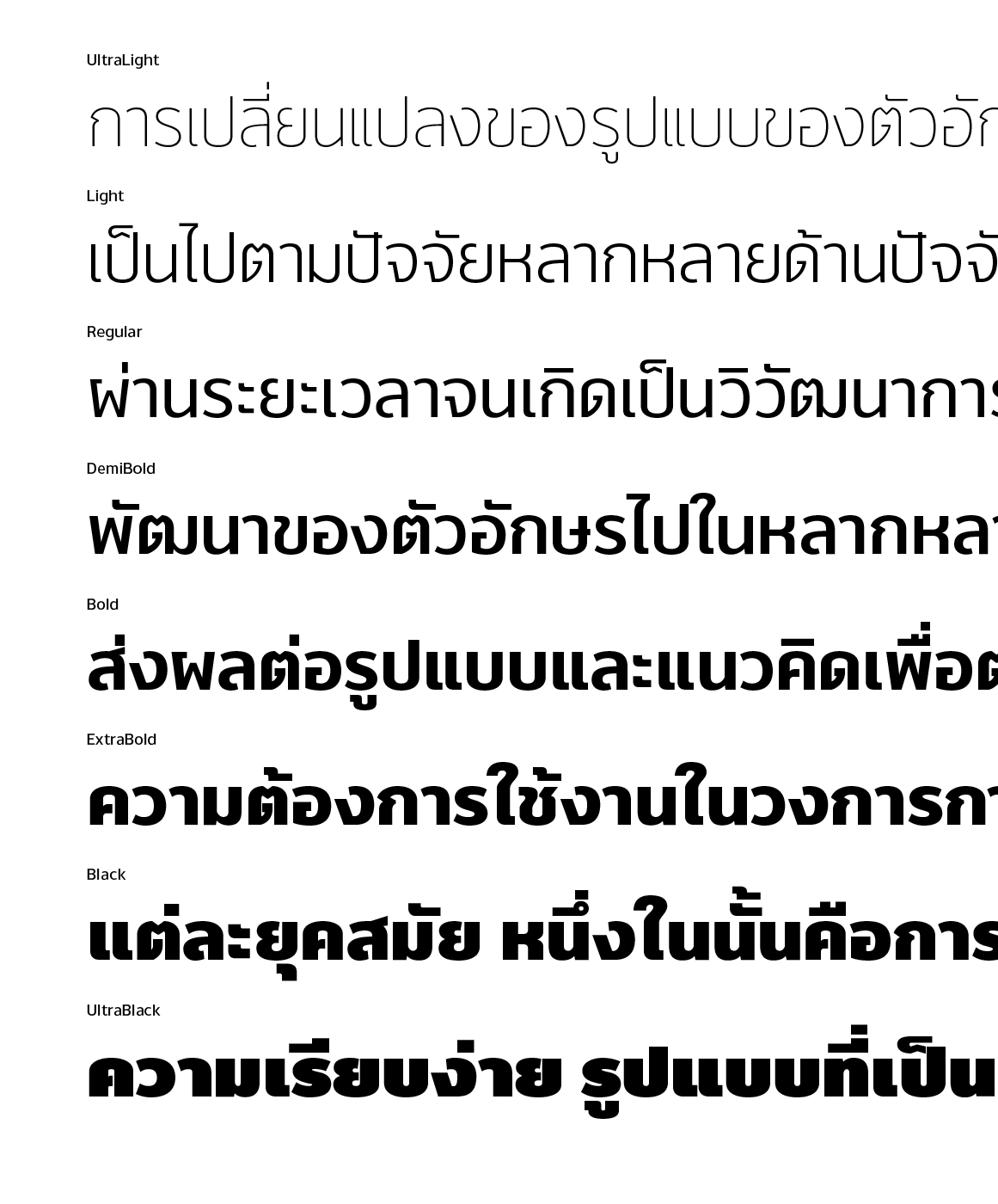
Anuyart
เพื่อตอบสนองความเรียบง่ายที่เข้ากันได้ดีอย่างกลมกลืนในงานออกแบบ “อนุญาต” เป็นตัวพิมพ์ที่ถูกพัฒนาจากตัวอักษร Latin แบบ Sans-serif ที่มีความเรียบง่ายแต่ผสมผสานกับความเป็น Humanist Typeface จึงทำให้แบบตัวอักษรนี้ดูกลมกลืนและไม่แข็งกระด้างแบบเรขาคณิต เข้ากับบริบทในปัจุบันพร้อมรองรับการใช้งานสิ่งพิมพ์ งานดิจิตอล แบนเนอร์ หรือแม้แต่ใช้เป็นภาพลักษณ์องค์กรก็อยู่ในวิสัยที่เป็นไปได้ เพราะแบบตัวพิมพ์นี้ “อนุญาต” ให้ตอบสนองในทุกๆ งานออกแบบอยู่แล้ว
Name : Anuyart
Weight : UltraLight, Light, Regular, DemiBold, Bold, ExtraBold, Black and UltraBlack
Language : Latin 1 / Thai
Release Date : 2014
Designer : Suppakit Chalermlarp
Technician : Suppakit Chalermlarp